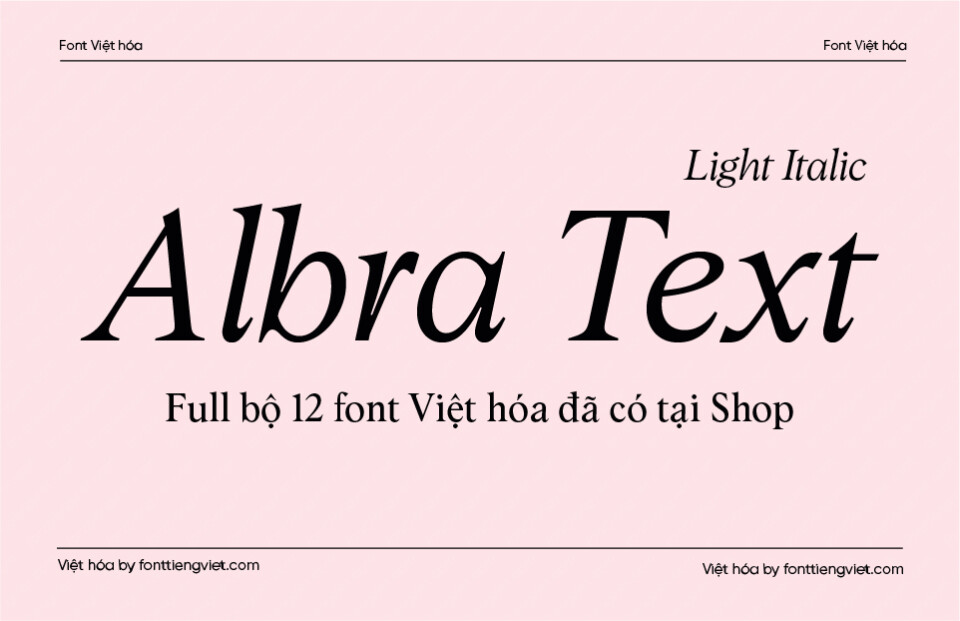
Font Việt hóa 1FTV VIP Albra Text Light Italic – Đỉnh Cao Nghệ Thuật Chữ Viết Cho Thiết Kế Hiện ĐạiGiới thiệu về Font Việt hóa 1FTV VIP Albra Text Light ItalicTrong thế giới thiết kế đồ họa ngày nay, việc lựa chọn một bộ Font Miễn Phí chất lượng không chỉ giúp truyền tải thông điệp mà còn khẳng định phong cách cá nhân của người sáng tạo. Một trong những cái tên đang thu hút sự chú ý của cộng đồng thiết kế tại Việt Nam chính là Font Việt hóa 1FTV VIP Albra Text Light Italic. Đây là một phiên bản đặc biệt thuộc bộ font Albra nổi tiếng, được tinh chỉnh và Việt hóa kỹ lưỡng nhằm đáp ứng nhu cầu sử dụng ngôn ngữ tiếng Việt một cách mượt mà và thẩm mỹ nhất. Với đặc điểm thanh mảnh nhưng không kém phần sắc sảo, bộ font này mang đến một cảm giác tinh tế, sang trọng và đầy tính nghệ thuật cho mọi bản thảo.Đặc điểm nổi bật của Font Việt hóa 1FTV VIP Albra Text Light ItalicPhong cách thiết kế Serif hiện đạiFont Việt hóa 1FTV VIP Albra Text Light Italic thuộc dòng chữ Serif (có chân) nhưng được thiết kế theo phong cách hiện đại. Sự kết hợp giữa các đường nét thanh mảnh của biến thể “Light” và độ nghiêng đặc trưng của “Italic” tạo nên một nhịp điệu uyển chuyển cho văn bản. Điều này giúp cho các đoạn văn bản dài trở nên dễ đọc hơn, đồng thời tạo ra một điểm nhấn thị giác độc đáo cho người xem ngay từ cái nhìn đầu tiên.Khả năng hiển thị tối ưu trên nhiều nền tảngMột ưu điểm lớn của Font Việt hóa 1FTV VIP Albra Text Light Italic chính là khả năng hiển thị xuất sắc. Dù bạn sử dụng trong các ấn phẩm in ấn như tạp chí, sách báo hay các thiết kế kỹ thuật số trên website và mạng xã hội, bộ font này vẫn giữ được độ sắc nét cực cao. Các dấu câu tiếng Việt được đặt vị trí chuẩn xác, không bị lỗi đè dấu hay khoảng cách không đều, giúp quy trình thiết kế trở nên chuyên nghiệp và nhanh chóng hơn rất nhiều.Ứng dụng thực tế của bộ font trong đời sống và học tậpSử dụng trong giáo dục và trình bày tiểu luậnĐối với học sinh và giáo viên, việc sử dụng Font Việt hóa 1FTV VIP Albra Text Light Italic giúp các bài thuyết trình hay tài liệu giảng dạy trở nên trang trọng hơn. Thay vì sử dụng những phông chữ mặc định khô khan, sự mềm mại của Albra Text Light Italic sẽ làm cho các tiêu đề hoặc các đoạn trích dẫn quan trọng trở nên nổi bật, giúp người đọc dễ dàng tiếp thu kiến thức một cách hứng thú.Sáng tạo nội dung số và nhận diện thương hiệuCác bạn trẻ làm sáng tạo nội dung trên Canva hay Adobe Photoshop chắc chắn sẽ yêu thích bộ font này. Nó cực kỳ phù hợp cho các thiết kế thiệp mời, bìa sách, hay các bài đăng chia sẻ kiến thức trên mạng xã hội. Sự thanh thoát của nó giúp thương hiệu cá nhân của bạn trông cao cấp và có gu thẩm mỹ riêng biệt.Kết luận và cách sở hữu bộ font chất lượngCó thể khẳng định rằng, Font Việt hóa 1FTV VIP Albra Text Light Italic là sự lựa chọn hoàn hảo cho những ai đang tìm kiếm vẻ đẹp cổ điển pha lẫn tinh thần đương đại. Việc sử dụng font chữ này không chỉ giúp bài viết của bạn chuyên nghiệp hơn mà còn tôn vinh vẻ đẹp của tiếng Việt qua từng nét chữ. Nếu bạn đang tìm kiếm những tài nguyên thiết kế tối ưu, hãy truy cập ngay vào Font Miễn Phí, Font Việt Hóa, Font Việt hóa 1FTV VIP Albra Text Light Italic để tải về và trải nghiệm sức mạnh sáng tạo mà bộ font này mang lại cho dự án của mình nhé.
Font Việt hóa 1FTV VIP Albra Text Light Italic